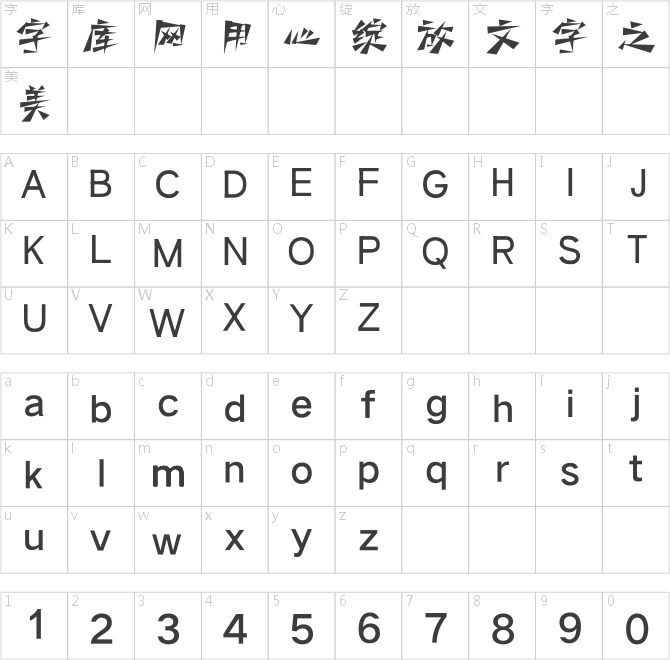
三極尖叫體筆畫設(shè)計(jì)為直線、斜線既有方向性又有力度的三角形圖形,挺拔、有力等形式心里特征,尖銳而收費(fèi)自如,創(chuàng)意卓越,個(gè)性突出。易于識別,便于應(yīng)用。
三極尖叫體字體SJjianjiao-Regular字庫是一款讓人賞心悅目、百看不厭的中文字體,適合各類廣告和產(chǎn)品包裝設(shè)計(jì)應(yīng)用,字體大小1.44MB,格式為ttf字體,上傳用戶是三極字庫,作者/版權(quán)方為三極字庫/歐偉